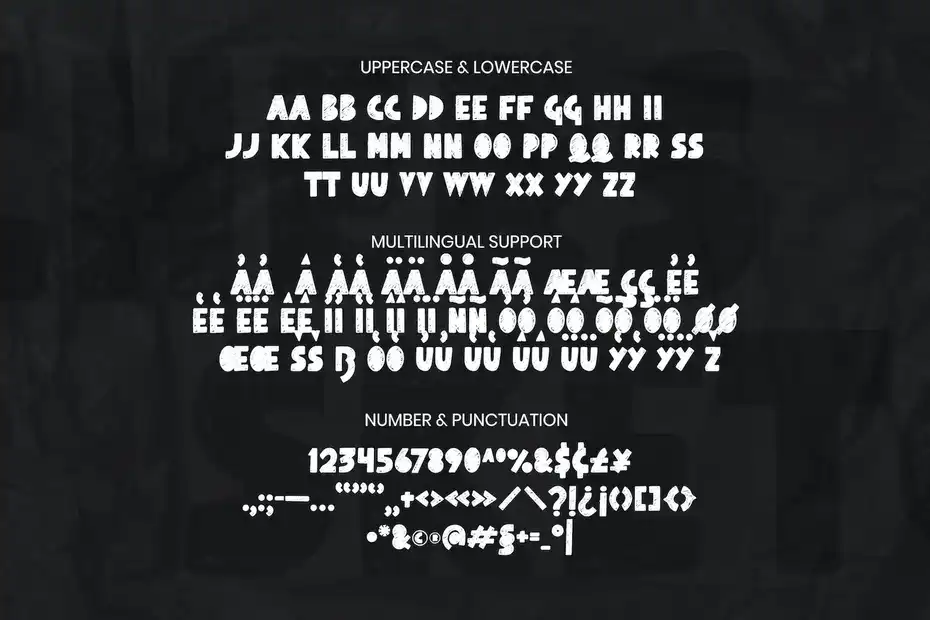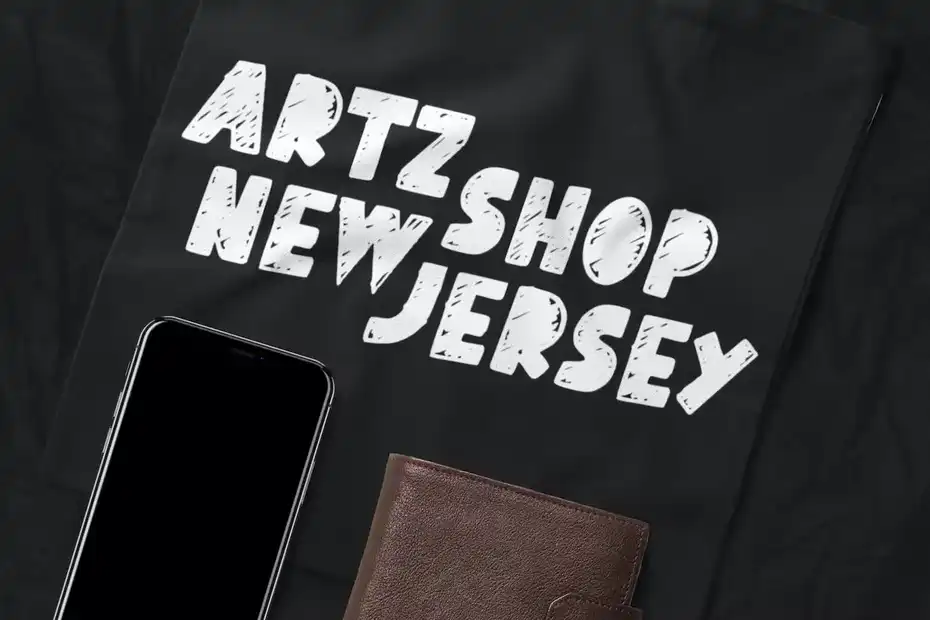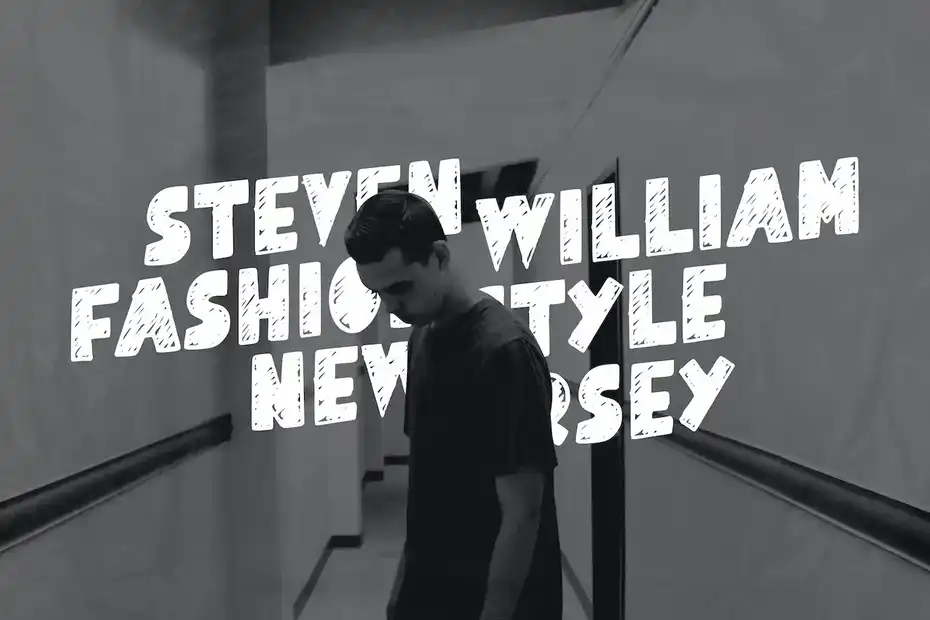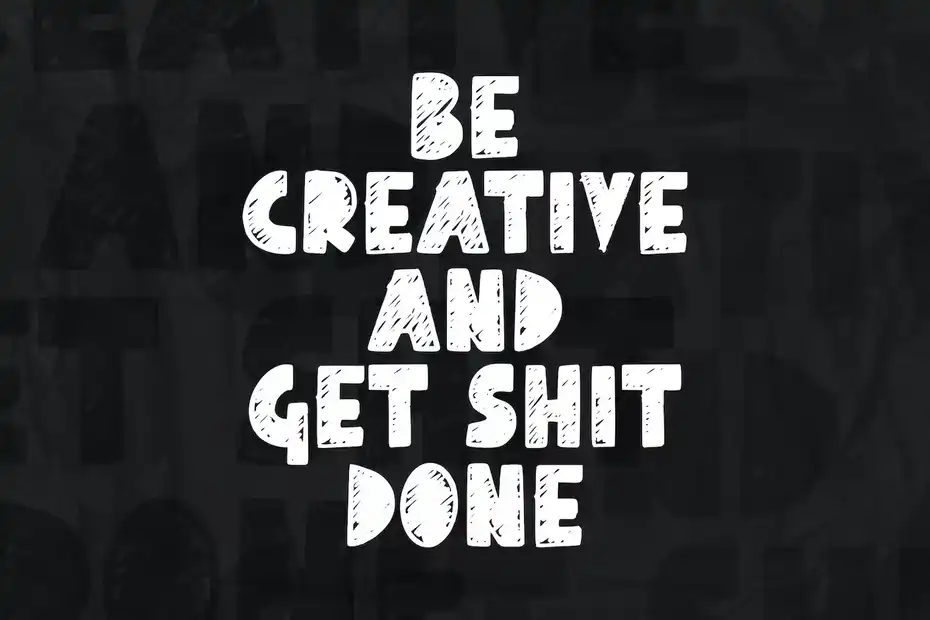
دانلود فونت اسکچ Sketchers – Sketch Font
دانلود فونت اسکچ Sketchers – Sketch Font : این مجموعه شامل یک فونت انگلیسی Sans-Serif با طرح اسکچ است که برای لوگو، نام تجاری، کتاب، تیشرت، مجله، کارت تبریک، تیتر و غیره مناسب
• عنوان مجموعه: Sketchers – Sketch Font